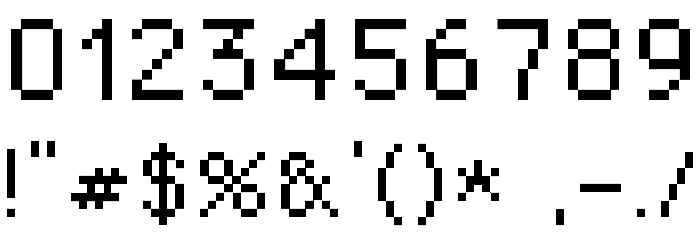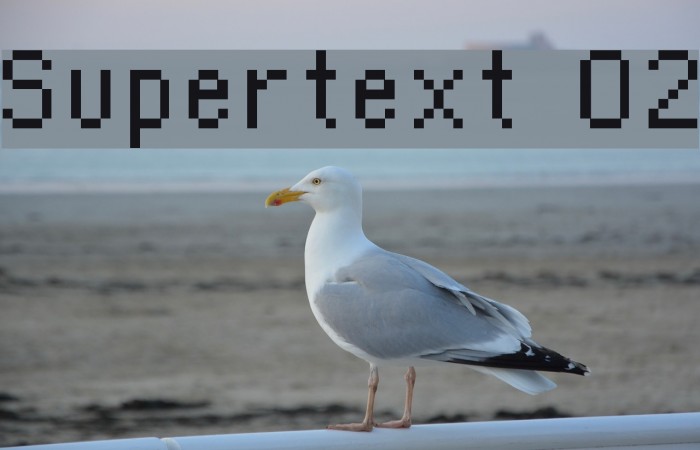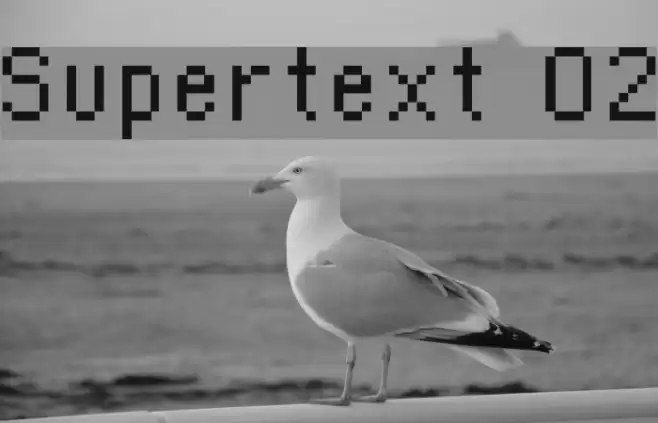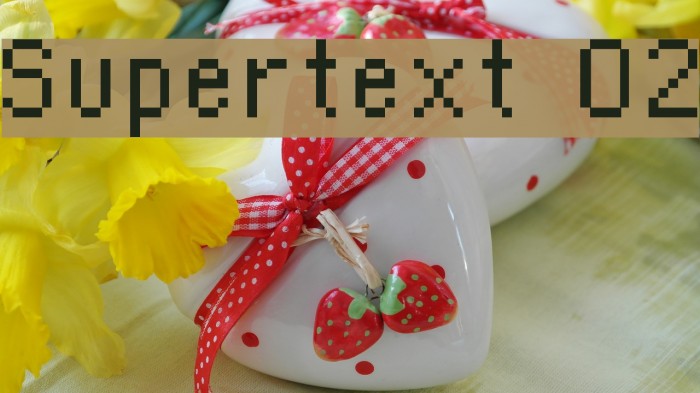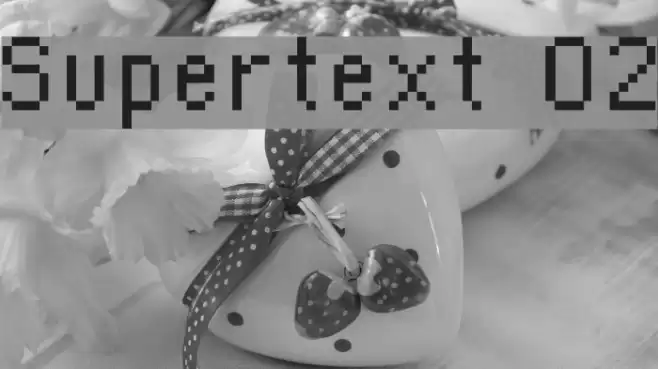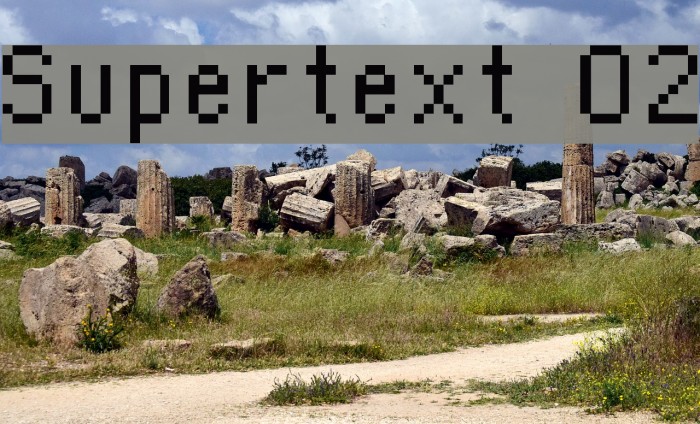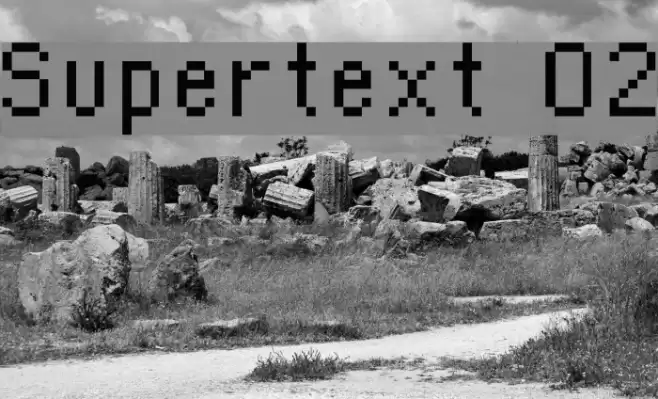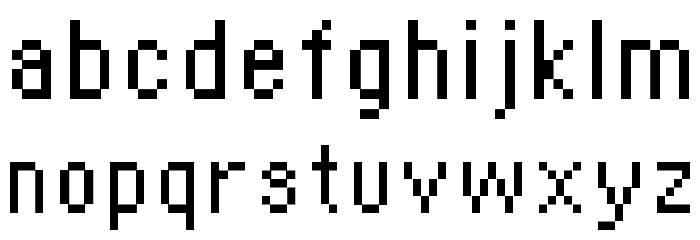
Supertext 02 Font
Font by Sven Stuber - www.superlooper.de
| Gesamtstil | Retro, Digital |
| Anwendungsfall | Headlines, Logos, Digital displays |
| Vorgeschlagene Projekte | Ideal for retro-themed designs, video game graphics, digital art projects, and any creative work seeking a nostalgic or tech-inspired look. |